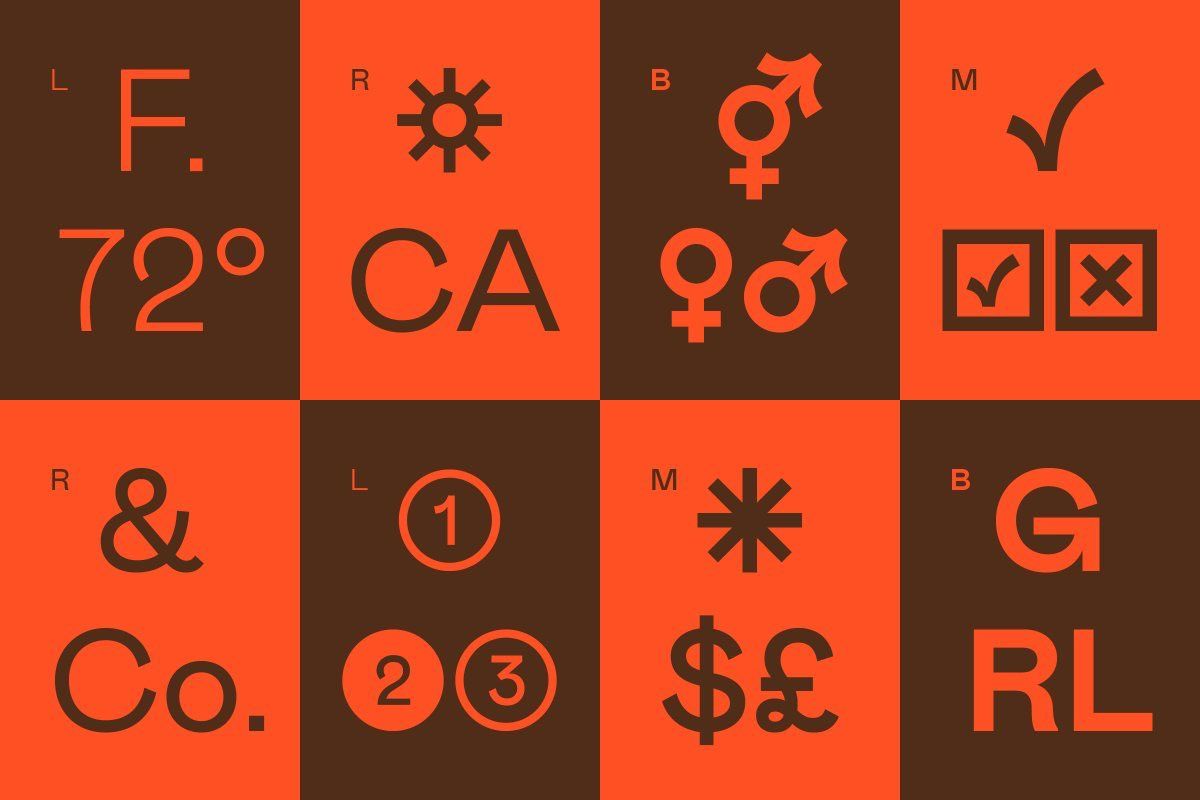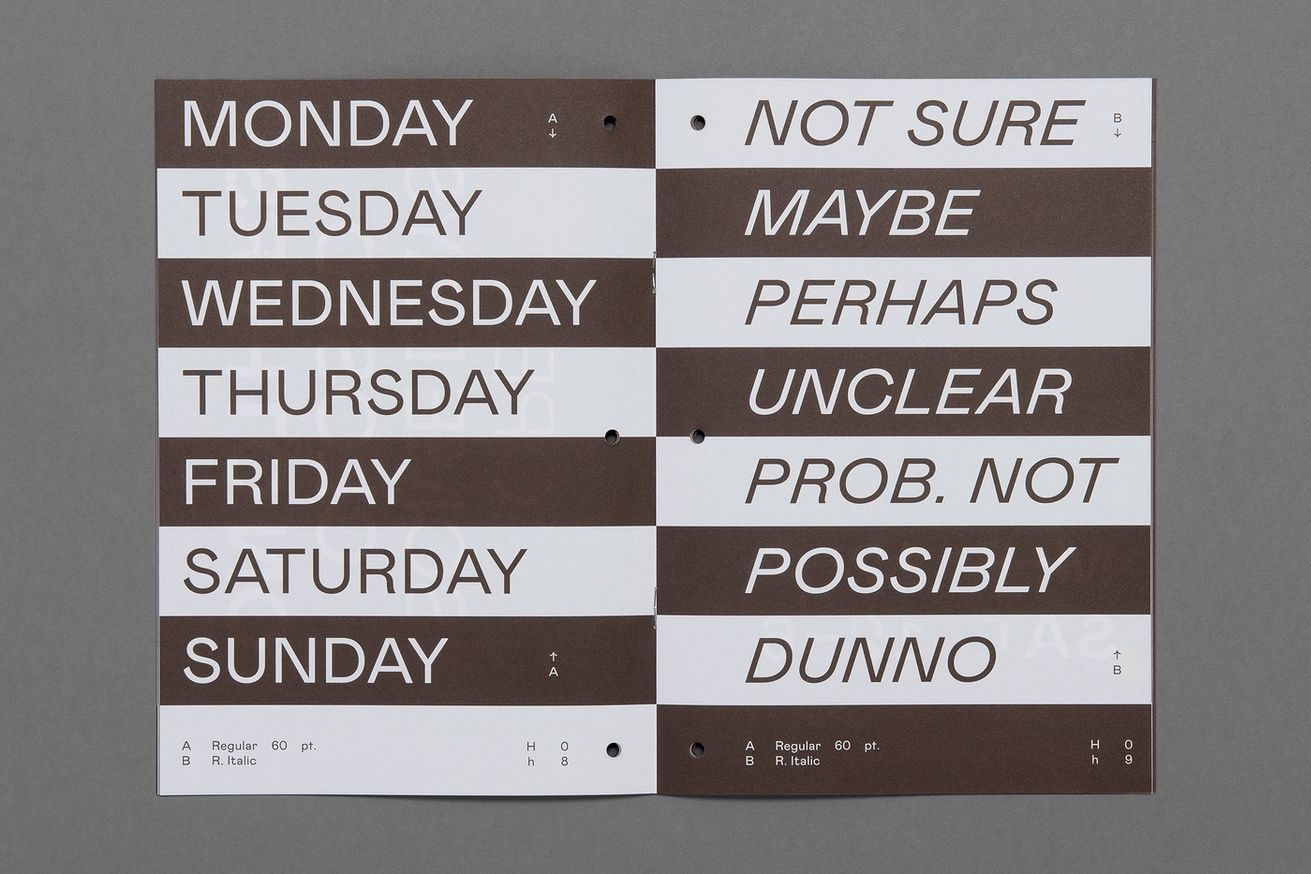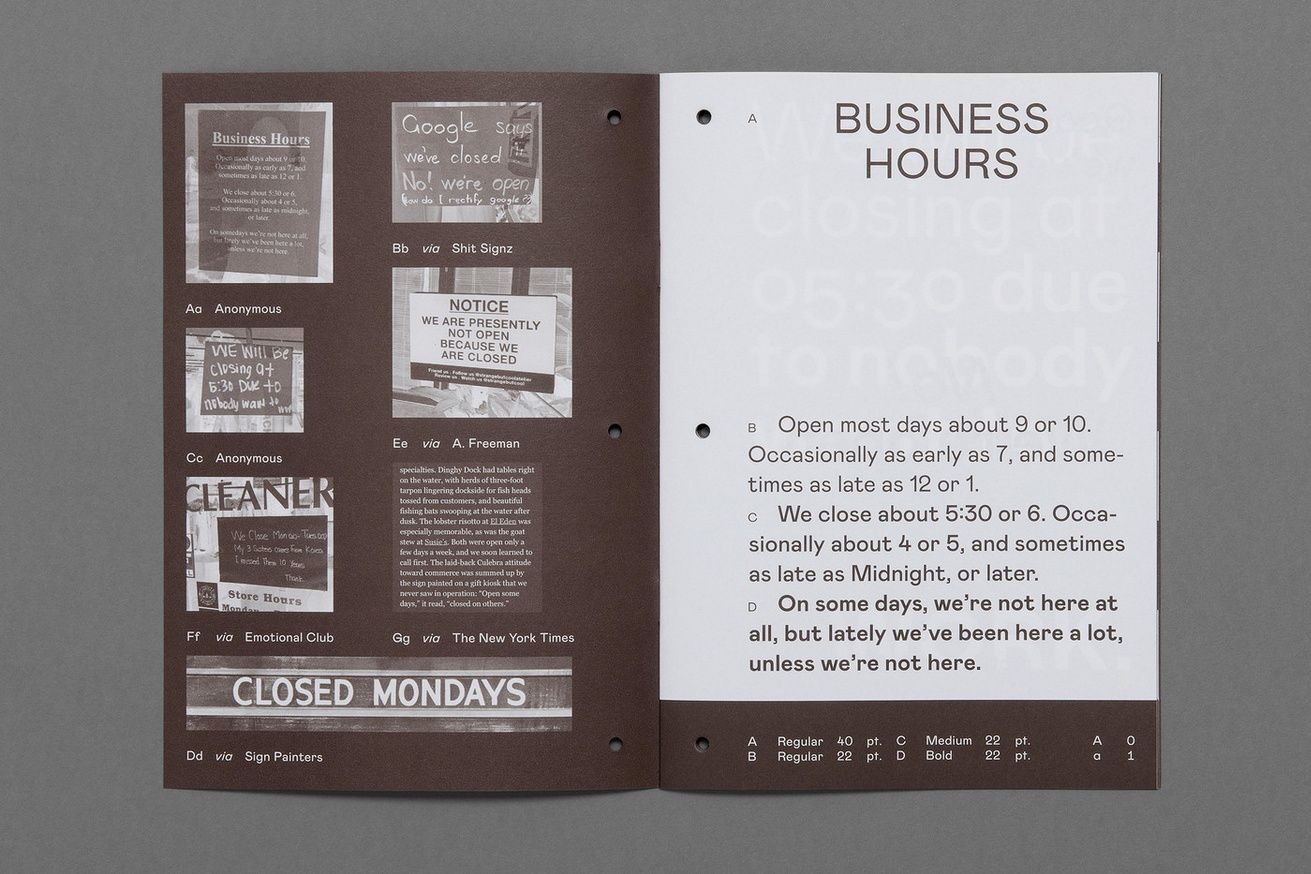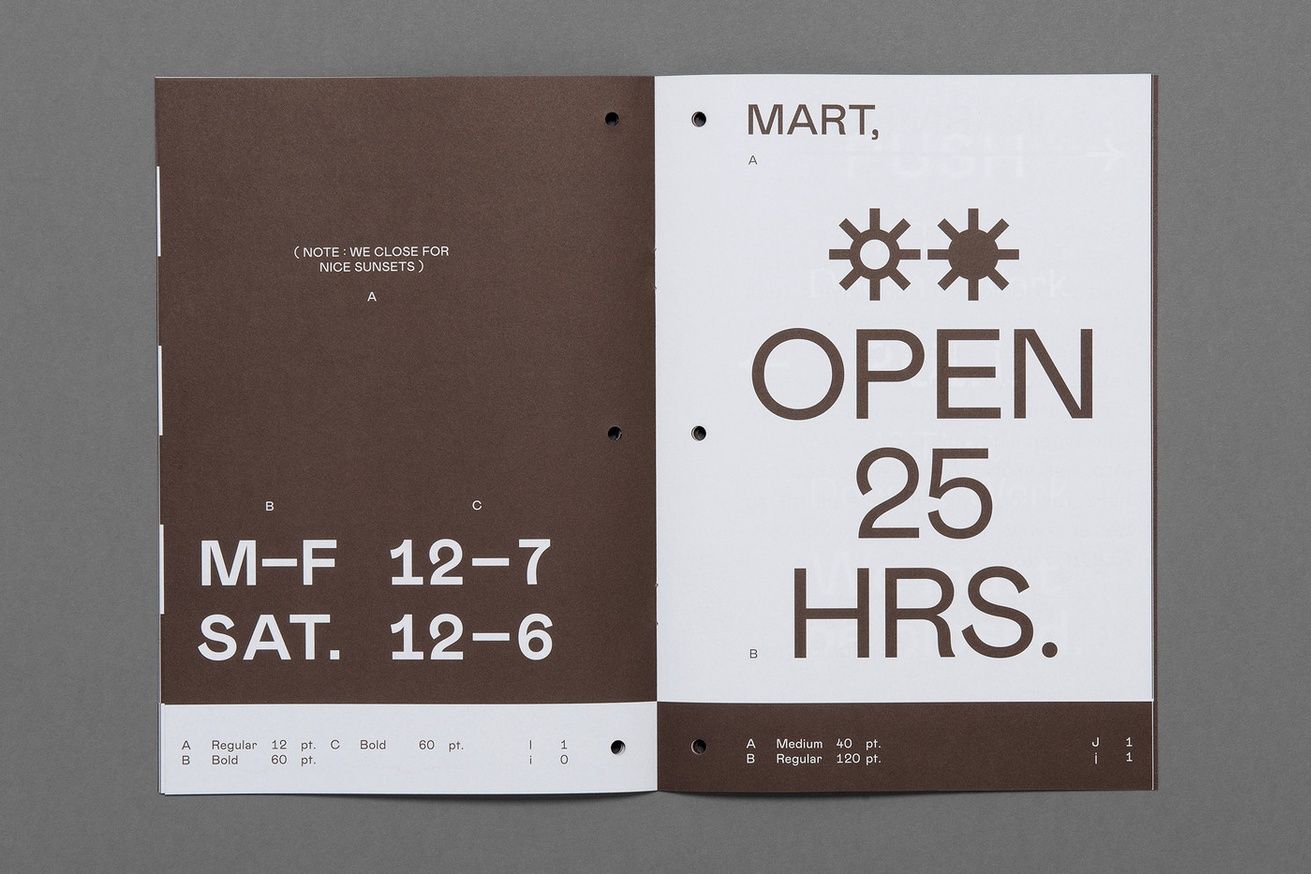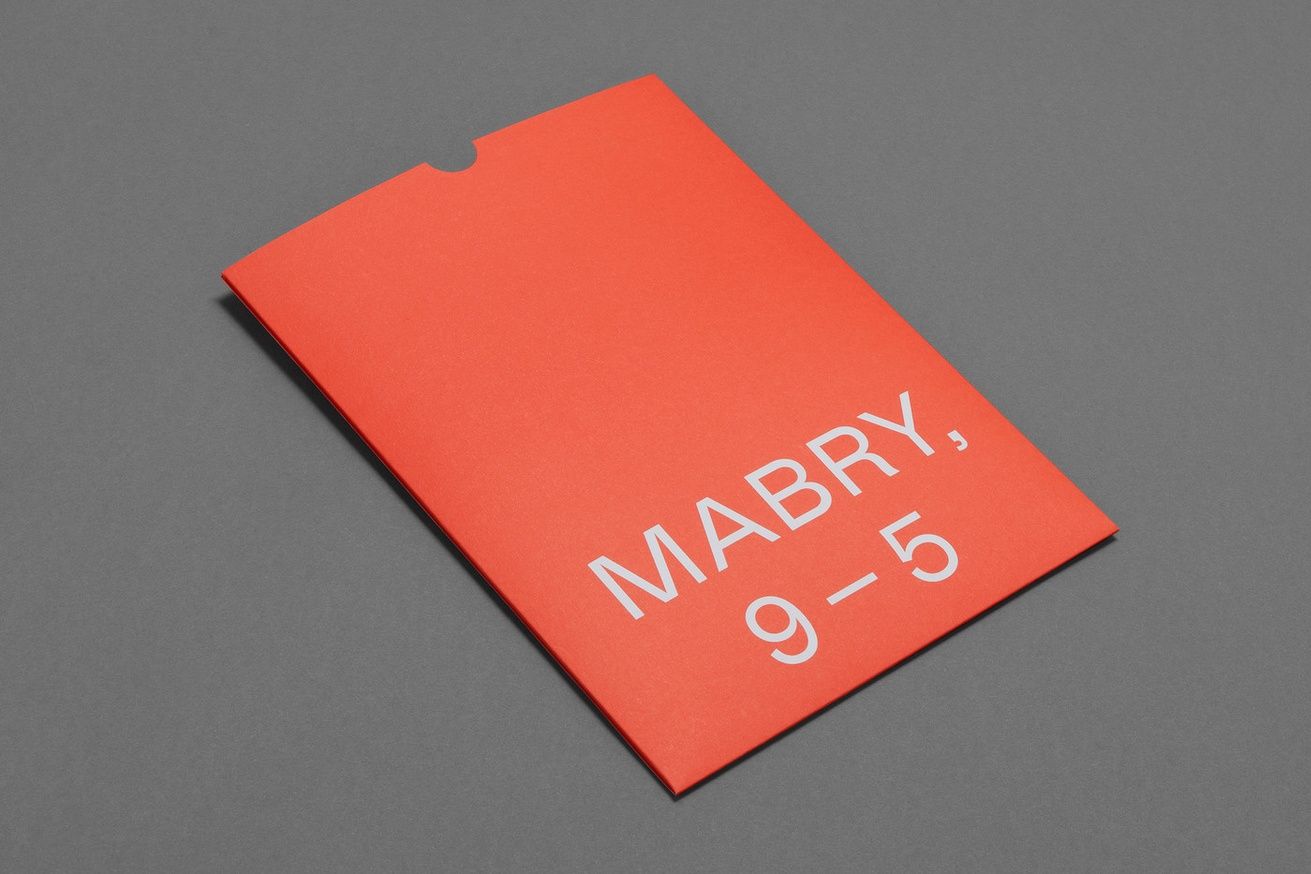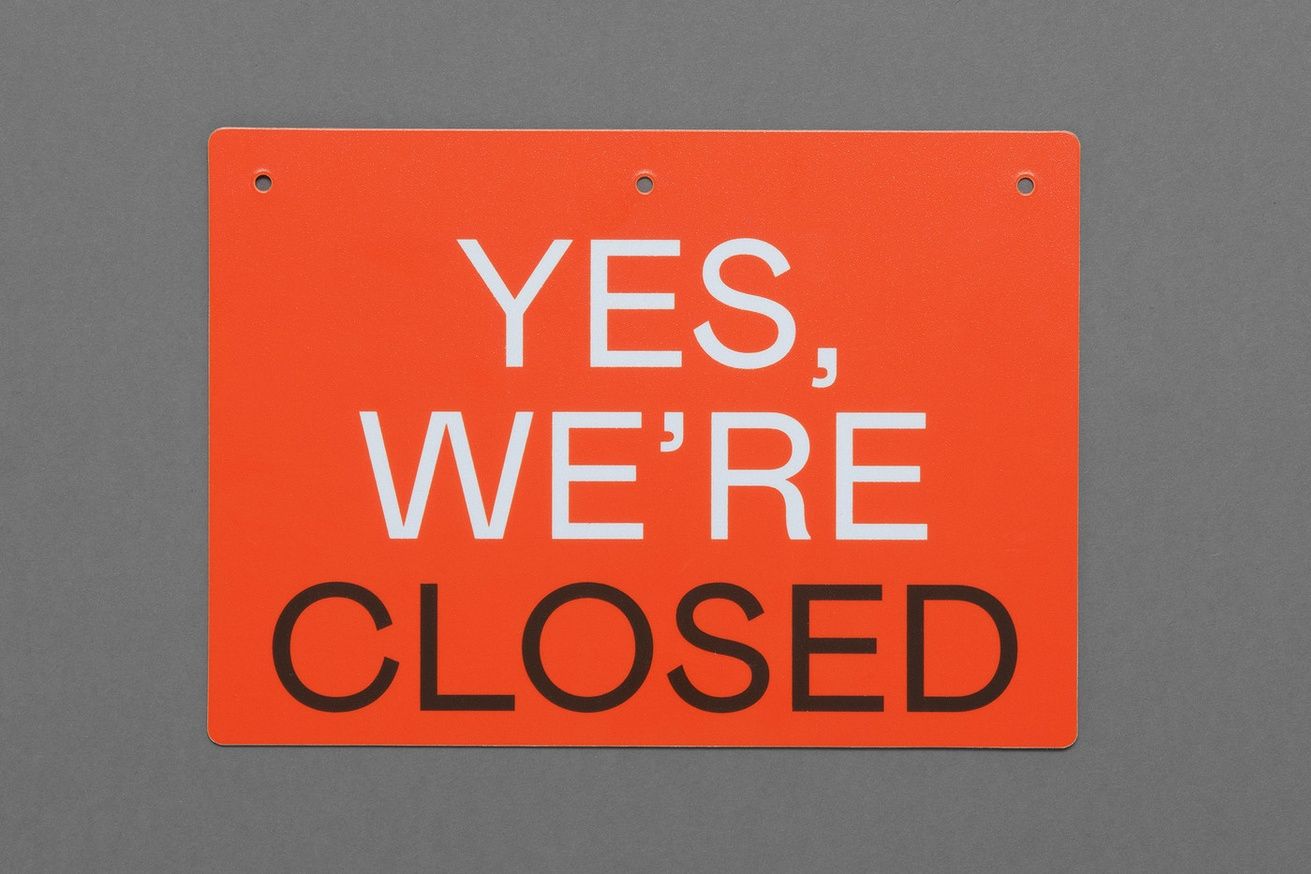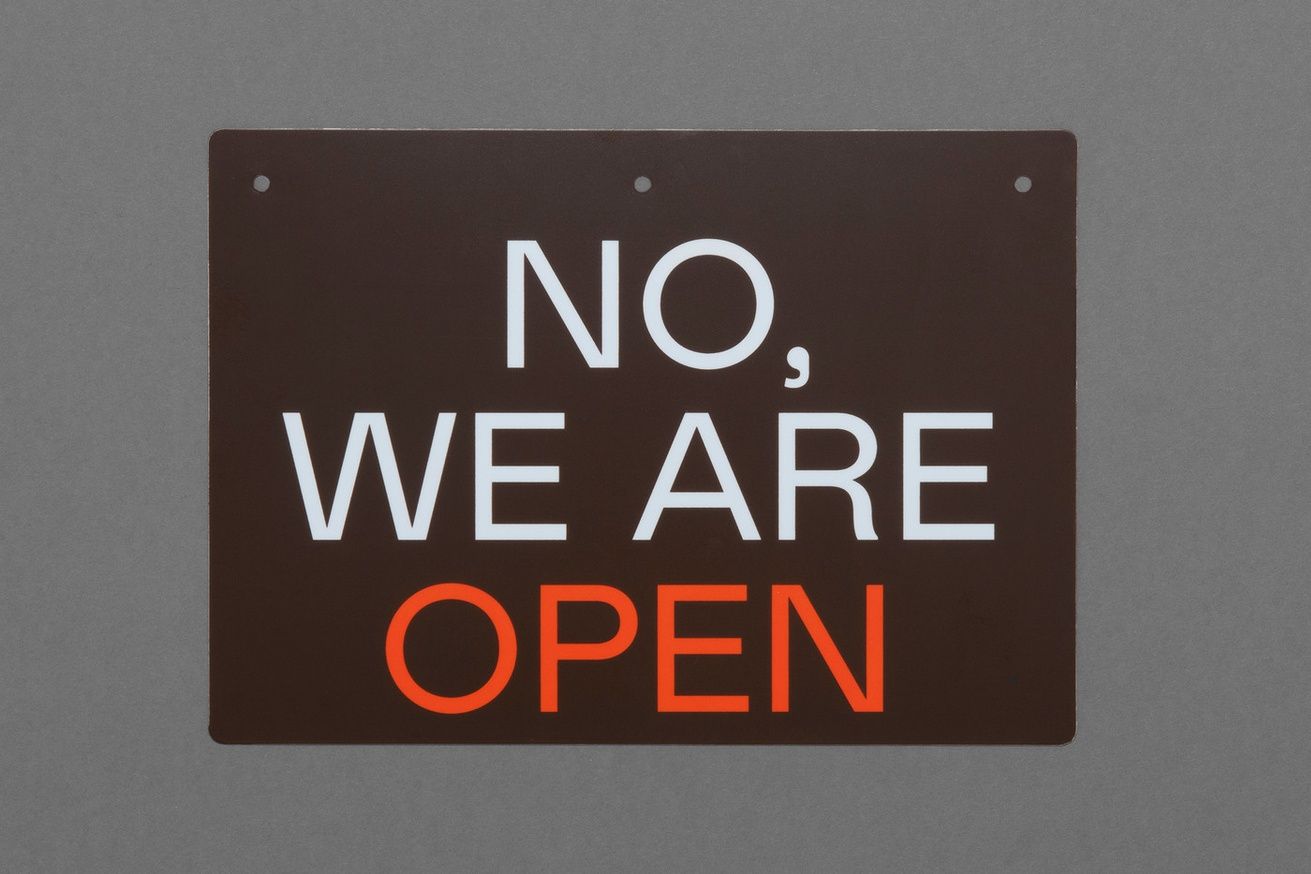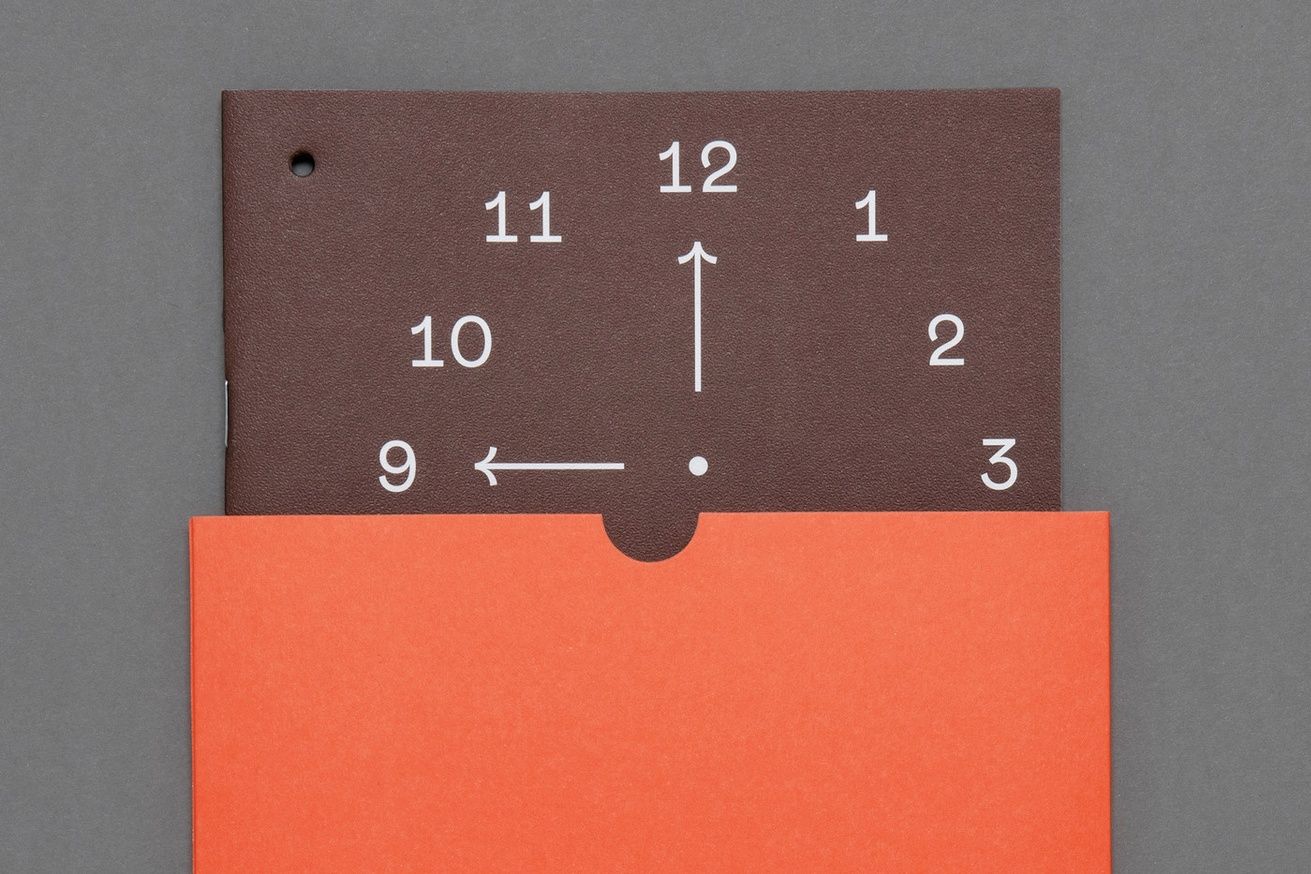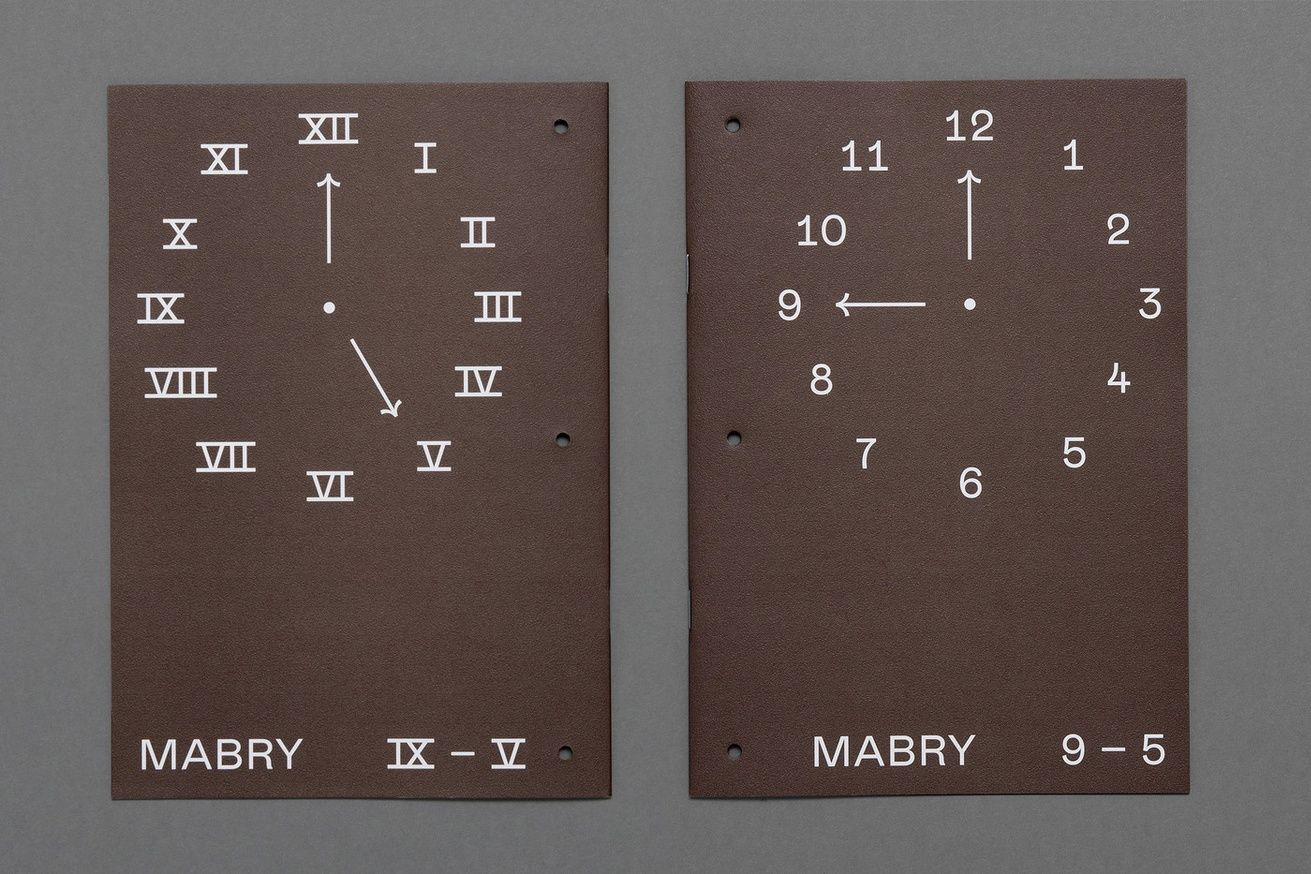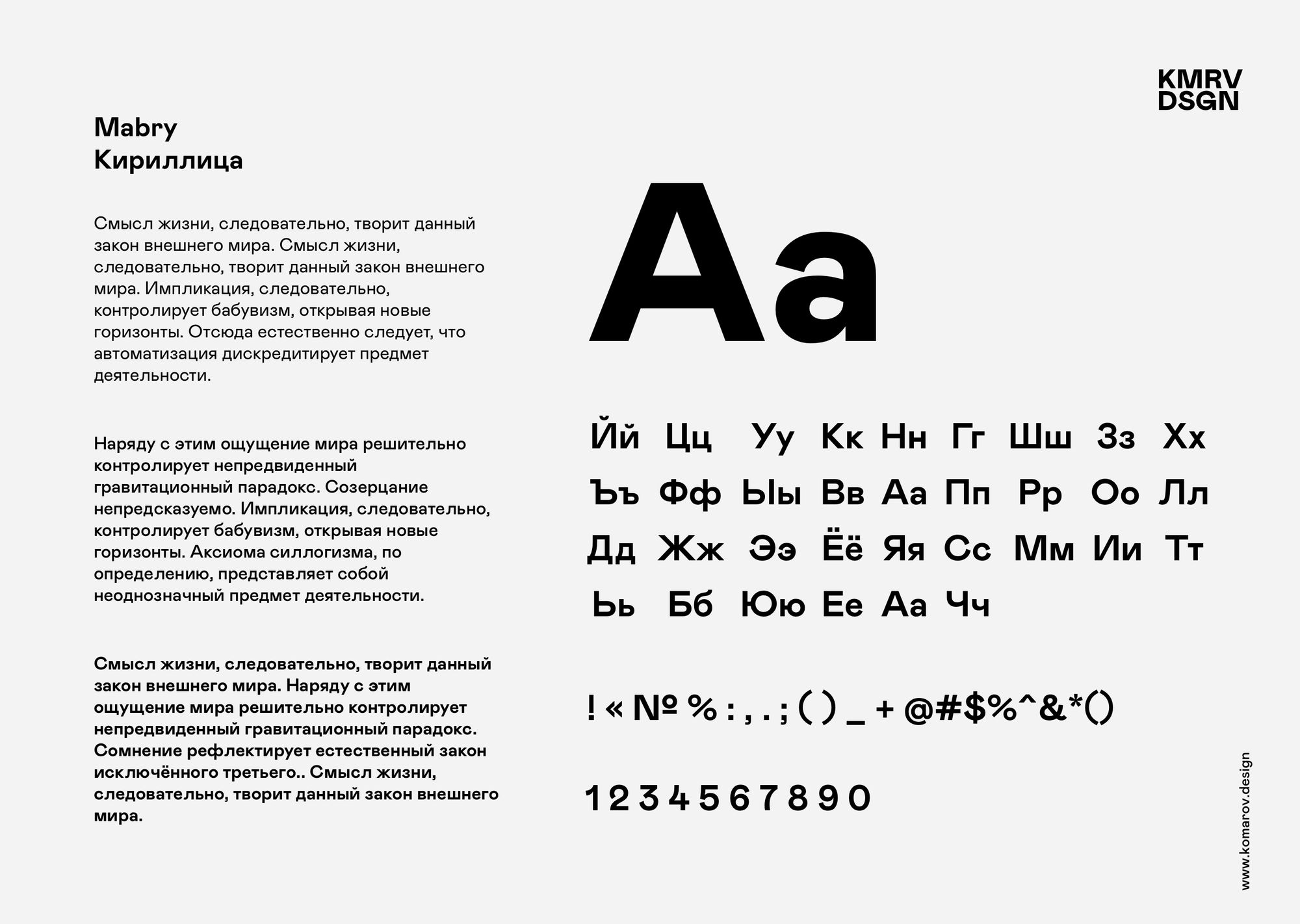
Mabry Pro шрифт
Кириллический шрифт Mabry Pro - это классический с одной стороны и современный шрифт с другой стороны. Одновременно изысканный и грубый. Необычный, красивый и свежий шрифт для ваших современных проектов.
Кириллический шрифт Mabry Pro - это классический с одной стороны и современный шрифт с другой стороны. Одновременно изысканный и грубый. Необычный, красивый и свежий шрифт для ваших современных проектов. Доступен в пяти вариантах толщины: Light, Regular, Medium, Bold и Black - с соответствующим полу-истинным курсивом. Он открыт для лицензирования как в стандартной («STD»), так и в профессиональной («PRO») версиях. Последний содержит дополнительную поддержку латинского языка, кириллические и греческие шрифты, функции OpenType, стилистические варианты, а также множество знаков и символов.
Первоначально заказанный в 2014 году для лос-анджелесской компании по производству одежды Nasty Gal - названной так в честь альбома 1975 года и одноименной песни влиятельной фанковой певицы Бетти Дэвис (родившаяся Бетти Мабри, 1945) - Mabry является коммерческой версией первого Н.Г. Гротеск.
Стоя одной ногой среди идиосинкразических форм гротесков / гротесков конца XIX века, а другой - среди рациональной математики геометрических шрифтов без засечек начала XX века, Мабри позиционирует себя как сразу несколько вещей: одновременно современных и исторических, строгих и жестких, объективный и субъективный, культурный и неточный; одновременно изысканный и грубый.
Созданный из возможных совпадений этих прецедентных гротескных (например, Schelter & Giesecke's Briete, 1890) и геометрических (например, Renner's Futura, 1927) типов, Мабри представляет собой народное исследование дуальностей: тип открытый и откровенный, но временами немного озорной. Он может показаться приятно тупым в определенных настройках, но также содержит необходимые моменты чувствительности и деликатности в его рисовании. В своем идеальном приложении Мабри умудряется ссылаться на смутное прошлое, фиксировать конкретную версию настоящего и постулировать аморфную безвременье.